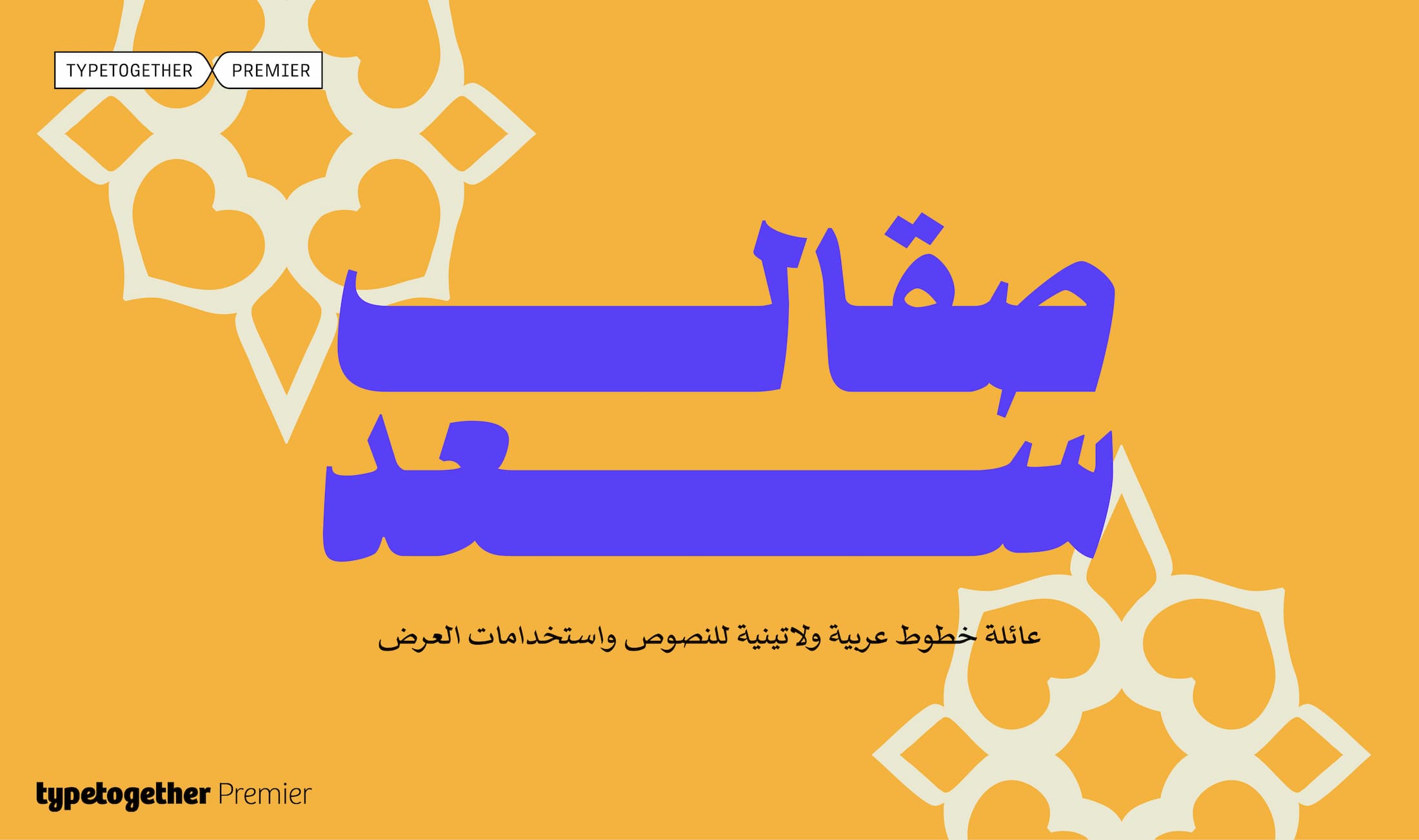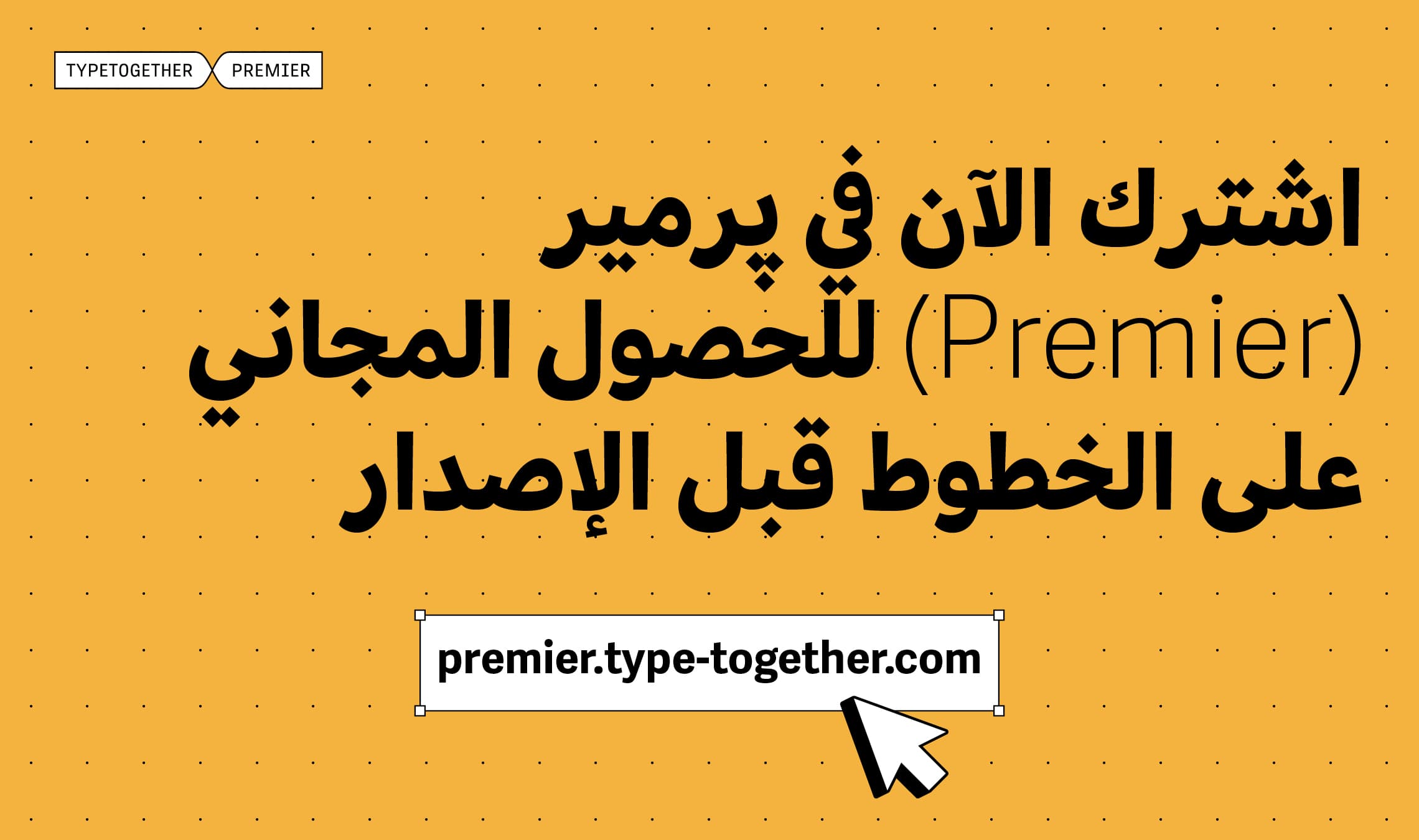
صقال سعد يصدر على تایپ توگذر پرمیر
يسعدنا أن نعلن عن إصدار صقال سعد (Sakkal Saad)، خط عربي يضم 12 أسلوبًا من تصميم الدكتور مأمون صقال و عائدة صقال! تجمع هذه العائلة بين عناصر التصميم التقليدية والحديثة: جماليات خطية متوازنة مع حِدّة ضربات القلم لتمنح مظهرًا معاصرًا دافئًا في الوقت نفسه. ملاحظة مهمة: الخط متوفر حاليًا حصريًا عبر تایپ توگذر پرمیر (TypeTogether Premier).
يُعَد صقال سعد مثاليًا للافتات والعلامات التجارية ونصوص القراءة الطويلة، خاصة عبر الإنترنت وفي الكتب والمجلات. أما صقال سعد پوستر فهو رائع للعناوين والإعلانات. ويأتي مع نسخة مخصصة من خط أنيتو (Aneto) للنصوص اللاتينية، ما يمنحه وضوحًا وأسلوبًا بصريًا متماسكًا في التصاميم متعددة اللغات.
Sakkal Saad Premier release
We are excited to announce the release of Sakkal Saad, an Arabic typeface with 12 styles by Dr. Mamoun Sakkal and Aida Sakkal! The family communicates through both traditional and modern design elements: calligraphic beauty balanced by sharp pen strokes for a contemporary look that carries a dose of warmth. Just one important detail: it is currently only available on TypeTogether Premier.
Sakkal Saad is ideal for signage, branding, and long text settings, especially online and in books and magazines. Sakkal Saad Poster is great for display and advertising. With an included custom version of Aneto for Latin-based text, it provides clarity and graphic style in multiscript design and communication,